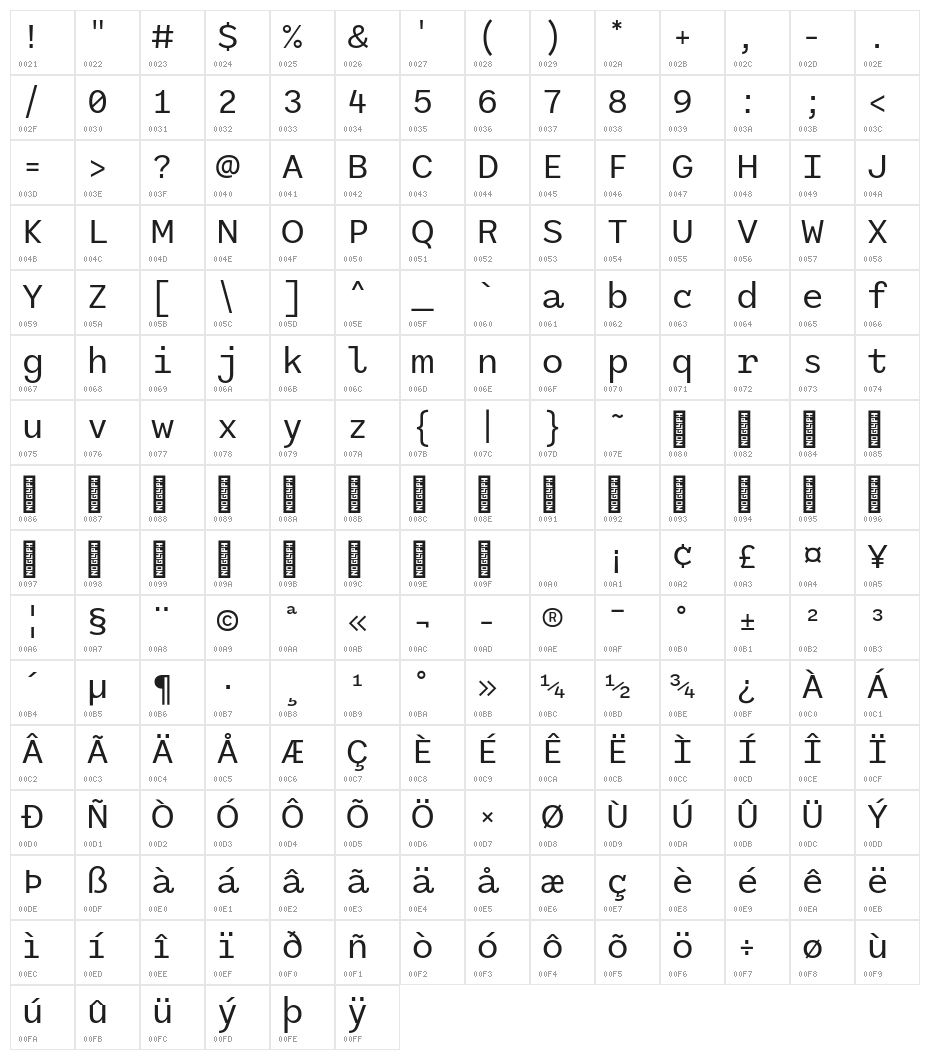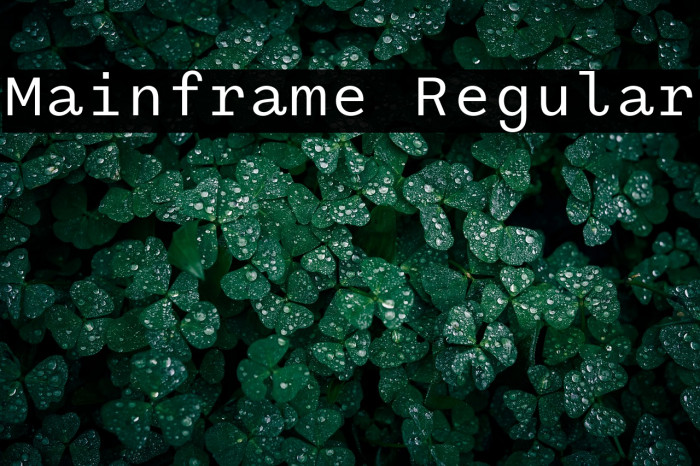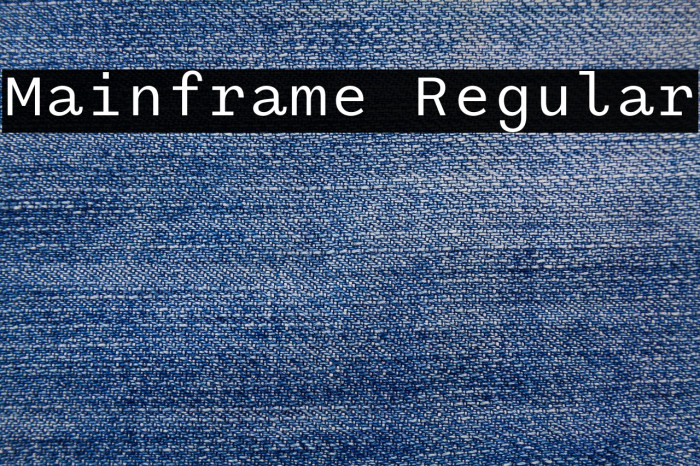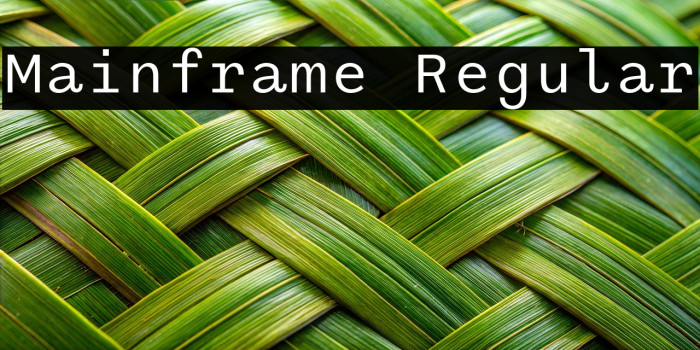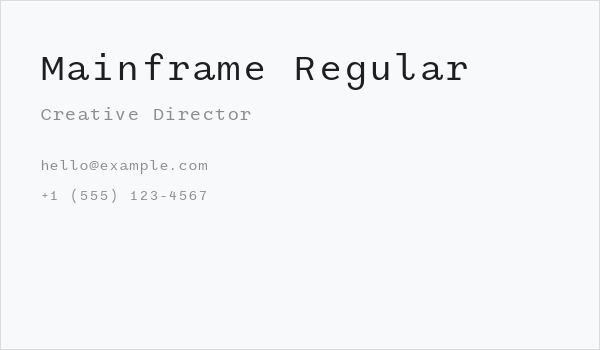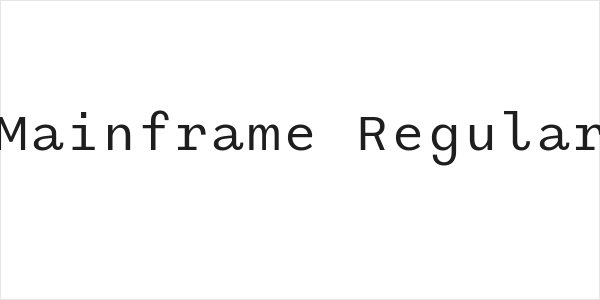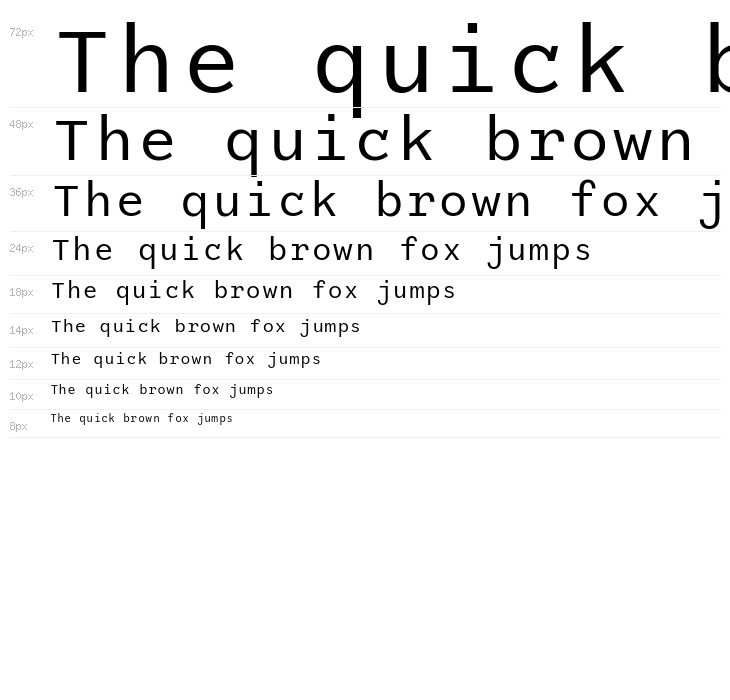
Mainframe Regular Font
| Caz de utilizare | Coding, Technical documentation, Digital interfaces |
| Proiecte propuse | Ideal for coding environments, technical documentation, and digital interfaces where clarity and precision are essential. |